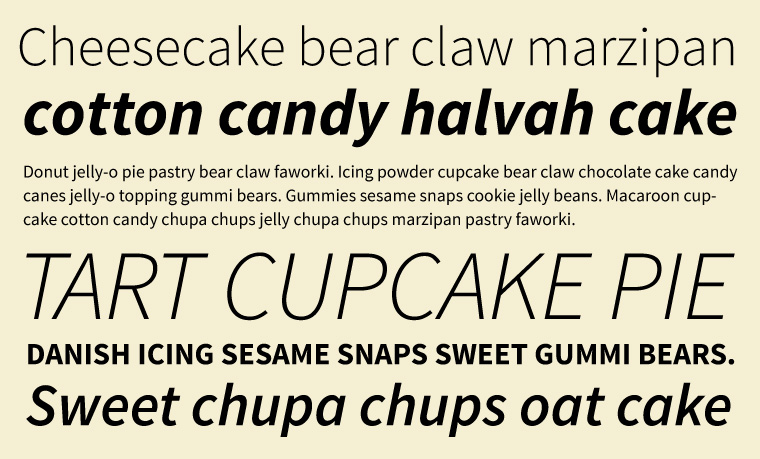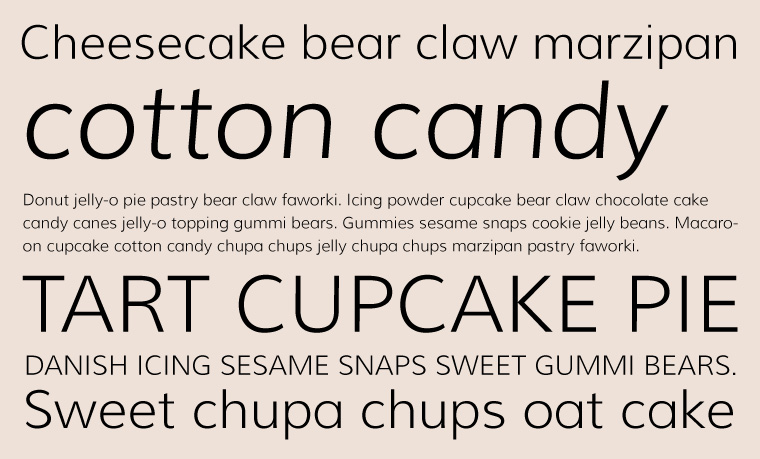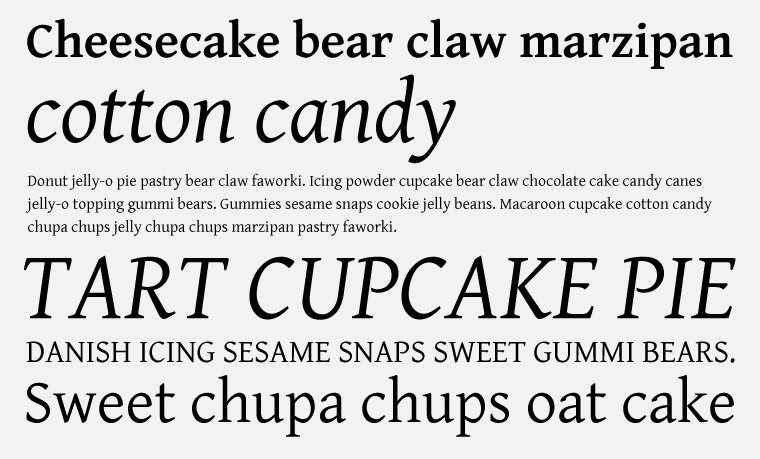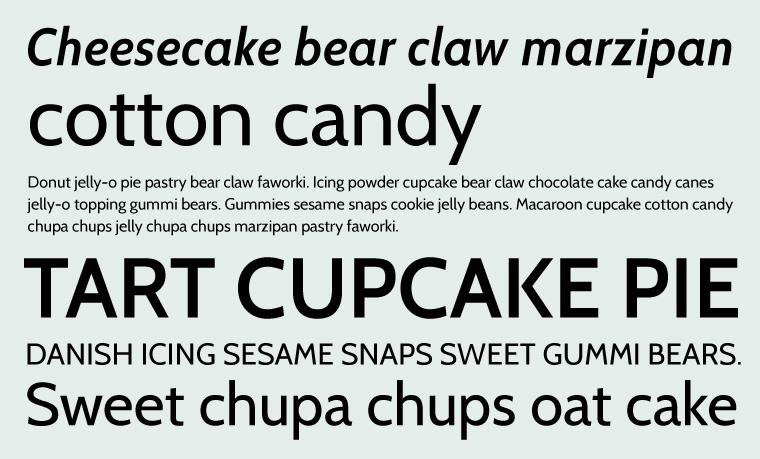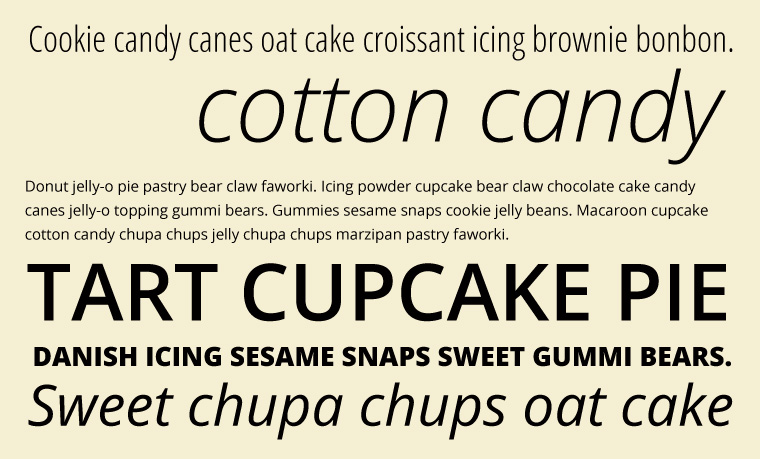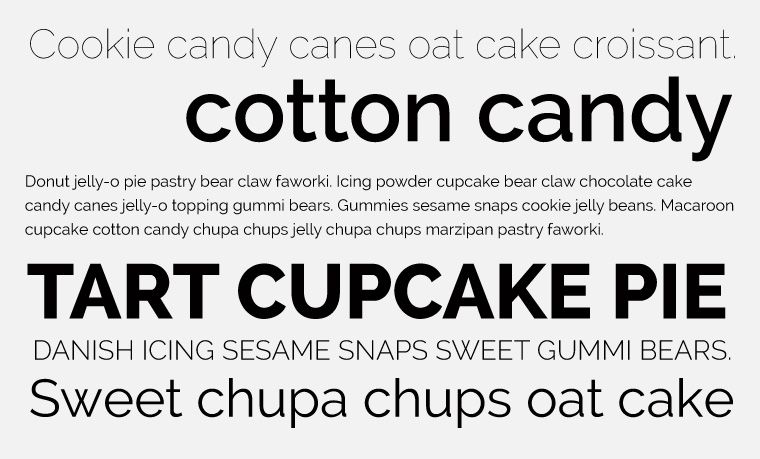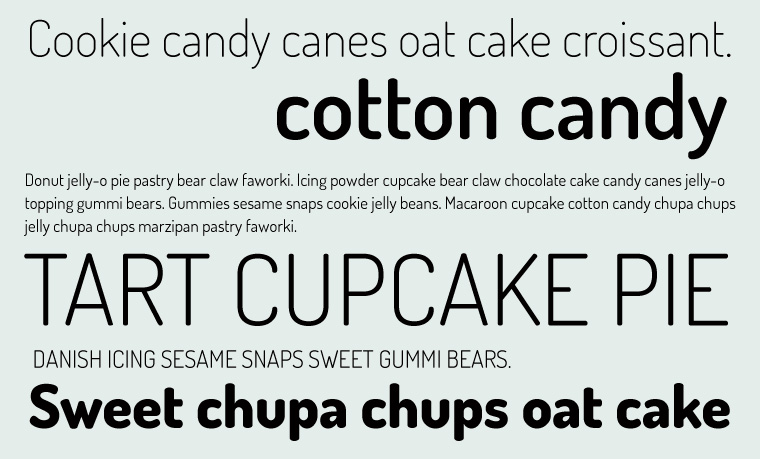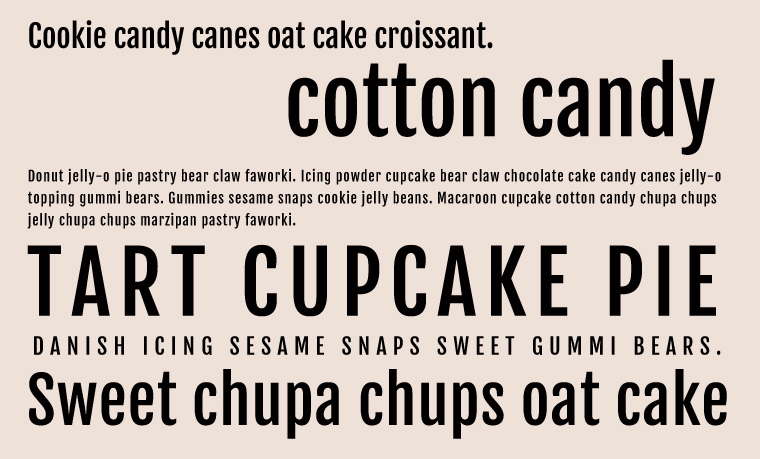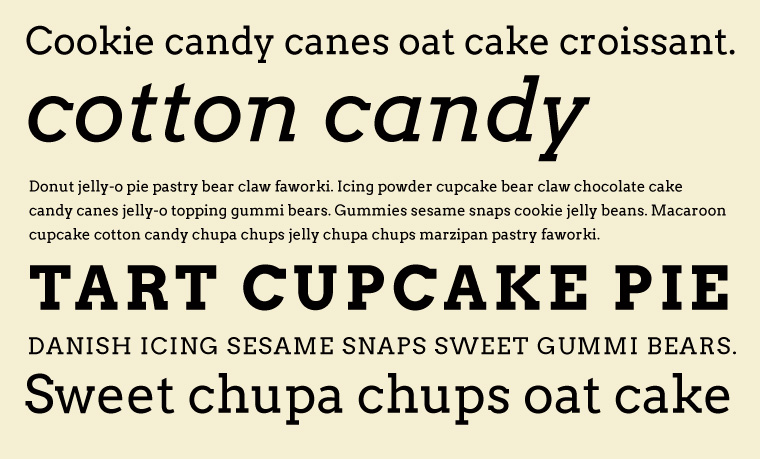
Meine Top 10 Google Webfonts für Webdesign-Projekte in 2013
Meine Top 10 Google Webfonts fuer 2013 Als Webdesigner ist man immer auf der Suche nach geeigneten, schönen Free-Fonts für neue Webdesigns und dank kostenloser Schriften-Ressourcen wie den Google Webfonts werden die Möglichkeiten glücklicherweise auch immer vielseitiger. Die Zeiten in denen Georgia, Arial und Verdana im Web dominiert haben sind also endlich vorbei (nichts gegen diese Schriften, aber etwas mehr Vielseitigkeit ist doch wünschenswert). Als Inspirationsquelle für mehr typografische Vielfalt in deinen Webdesigns hier eine kleine Sammlung meiner derzeitigen Google Web-Font Favoriten.
1. Source Sans Pro (sans-serif)
Source Sans Pro ist die erste Open-Source Schriftfamilie von Adobe. Die Schriftfamilie ist angenehm schlicht und modern und auf Grund der vielen Schriftschnitte (12 Schnitte von Light 200 bis Ultrabold 900) vielseitig einsetzbar. Source Sans Pro funktioniert prima als Fließtext-Schrift, funktioniert in Light oder Bold aber auch sehr gut als schlichte Überschrift.
2. Muli (sans-serif)
Die minimalistische und rund wirkende Muli gibt es in vier Schnitten (Book 300 und Normal 400, auch jeweils als Italic). Muli kann als moderne, schicke Fließtext-Schrift eingesetzt werden, mir selbst gefällt sie aber besonders für Überschriften.
3. Gentium Basic (serif)
Die Serifen-Schrift Gentium Basic in Normal und Bold (plus jeweils Italic) ist sehr angenehm lesbar und eignet sich daher vor allem, wenn man auf der Suche nach einer serifen Fließtext-Schrift ist. Die Schrift basiert auf der originalen Gentium-Schrift (von 2003) und ist ebenfalls vom Gentium-Schriftdesigner Victor Gaultney gestaltet. Die Gentium gibt es bei Google Webfonts auch noch als Gentium Book Basic.
4. Cabin (sans-serif)
Cabin ist eine sehr gerade, moderne serifenlose Schrift mit 8 Schnitten in der Schriftfamilie (von Normal 400 bis Bold 700). Cabin kann als moderner, serifenloser Fließtext oder auch für Überschriften eingesetzt werden.
5. Julius Sans One (sans-serif, Headlines)
Julius Sans One ist eine extravagante, schlanke Schrift für schicke, moderne Überschriften, Logos oder kurze Slogans geeignet von der Schrift-Foundry Latino Type. Es gibt nur einen Schriftschnitt (Normal 400). Wer nach etwas besonderem sucht, ist die Julius Sans One meiner Ansicht nach eine tolle Wahl.
6. Open Sans (sans-serif)
Die Open Sans ist in den letzten Monaten immer mehr zu einer Standard-Schrift im Web geworden und wird u.a. auch auf der WordPress.com Seite und im aktuellen WordPress Standard-Themes Twenty Twelve genutzt. Open Sans Schriftfamilie beinhaltet 10 Schnitte von Book 300 bis Extra-Bold 800.
7. Raleway (sans-serif)
Raleway ist eine weitere elegante und moderne serifenlose Schrift, die durch 9 Schnitte (Ultra-Light 100 bis Ultra-Bold 900) in der Schriftfamilie sehr vielseitig genutzt werden kann. Mir persönlich gefällt Raleway besonders gut in einem leichten Schnitt als Überschrift.
8. Dosis (sans-serif, Headlines)
Dosis ist eine abgerundete, recht schmale serifenlose Schrift für moderne Überschriften oder Slogans. Es gibt sie in 7 Schriftschnitten (von Light 200 bis Extra-Bold 800). Da Dosis sehr schmal ist, würde ich die Schrift nicht unbedingt für Fließtexte einsetzen.
9. Fjalla One (Display sans-serif, Headlines)
Wer eine fette, schmale Schrift für Überschriften sucht, könnte mit der Fjalla One glücklich werden. Es gibt zwar nur einen Schrift-Schnitt (Normal 400, wirkt eher fett) der Fjalla One, dieser ist meiner Ansicht nach aber eine interessante Alternative z.B. zur häufiger genutzten PT Sans Narrow.
10. Arvo (slab-serif, Headlines)
Arvo ist eine Charakter-starke Slab-Serifenschrift, die in vier Schnitten genutzt werden kann (Normal 400 und Bold 700, plus die jeweiligen Italic-Styles). Durch die Slab-Serifen ist Arvo sehr gut im Web lesbar und eignet sich sehr gut für Überschriften oder Intro-Texte bzw. Text-Slogans.